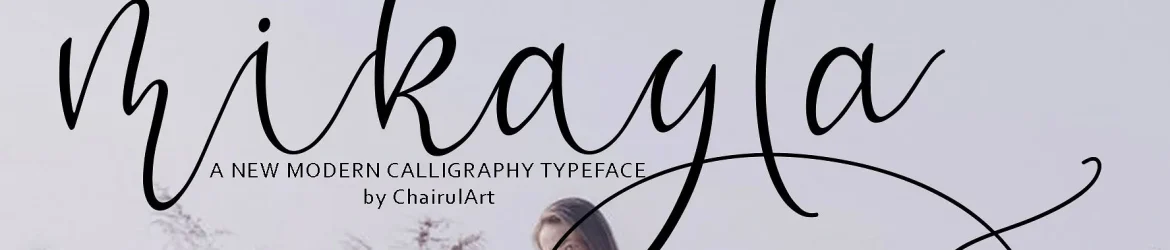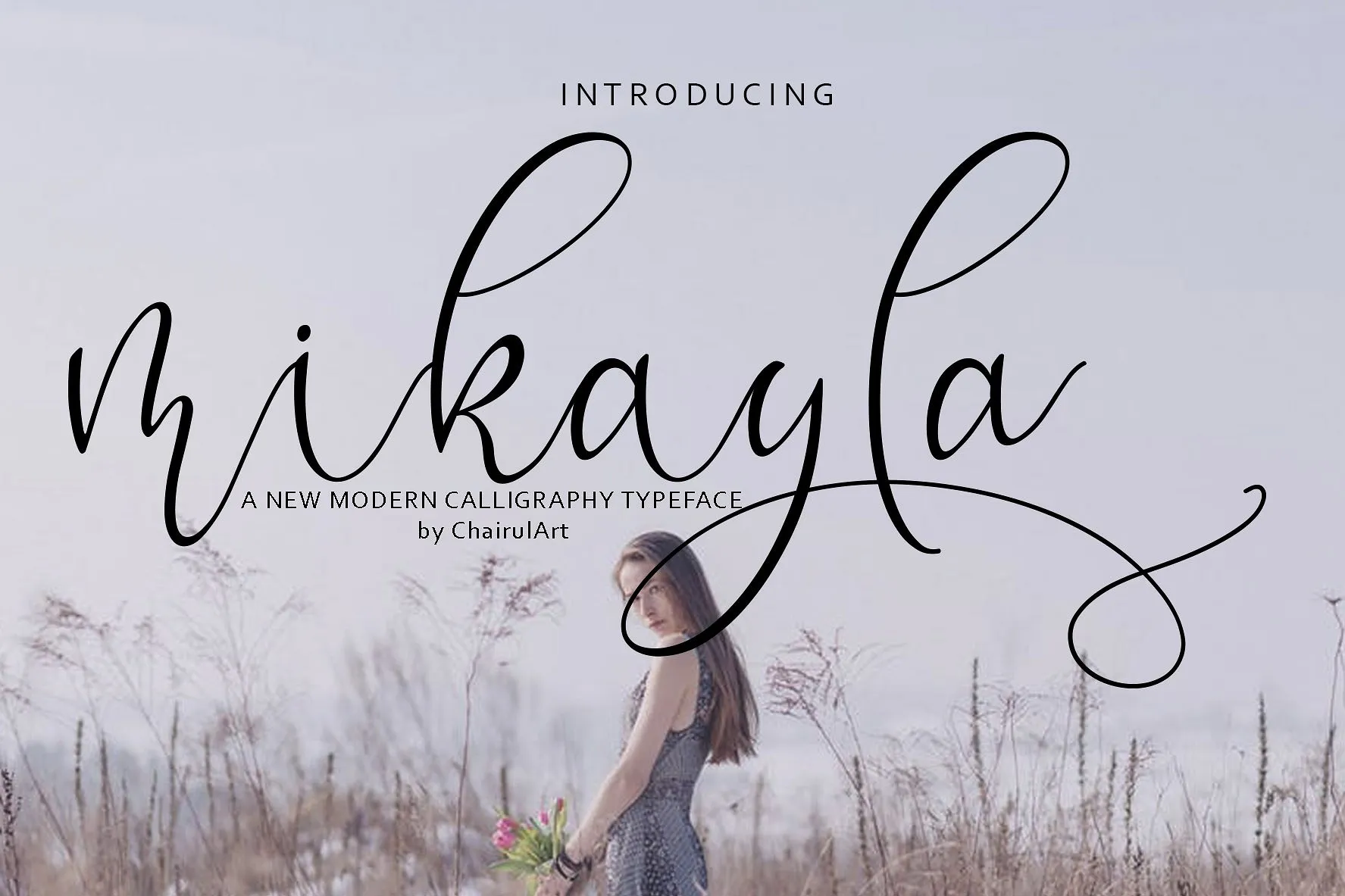
Mikayla Script Font – Fonte Grátis
Mikayla Script Font
A Mikayla Script Font é uma nova inovação que traz um tipo moderno e elegante com uma aparência simples e sofisticada. Desenvolvida por ChairulArt, esta fonte de script moderna foi projetada para oferecer textos incrivelmente atraentes e harmoniosos. A cada letra foi cuidadosamente criada para destacar o seu texto e dar-lhe um visual sofisticado e impecável. Ideal para uma ampla gama de projetos, como cartões de convite, cartazes, nomecards, frases inspiradoras, cabeçalhos de blog, marcações, logotipos, roupas, calçados, letras e decoração em geral. Com seu estilo moderno de script, a Mikayla Font é perfeitamente adequada para uma infinidade de usos. Ela não apenas adicionará um toque sofisticado a qualquer projeto, mas também permitirá que você personalize com facilidade o design de seu próprio modo. Seja em sua própria marca ou apenas dar um toque único ao texto de seus trabalhos, esta fonte é certamente uma escolha inteligente para tornar suas criações ainda mais singulares e únicas.